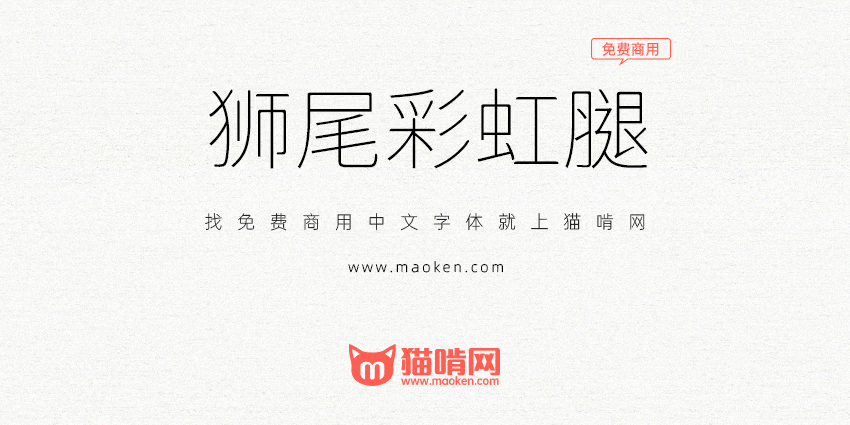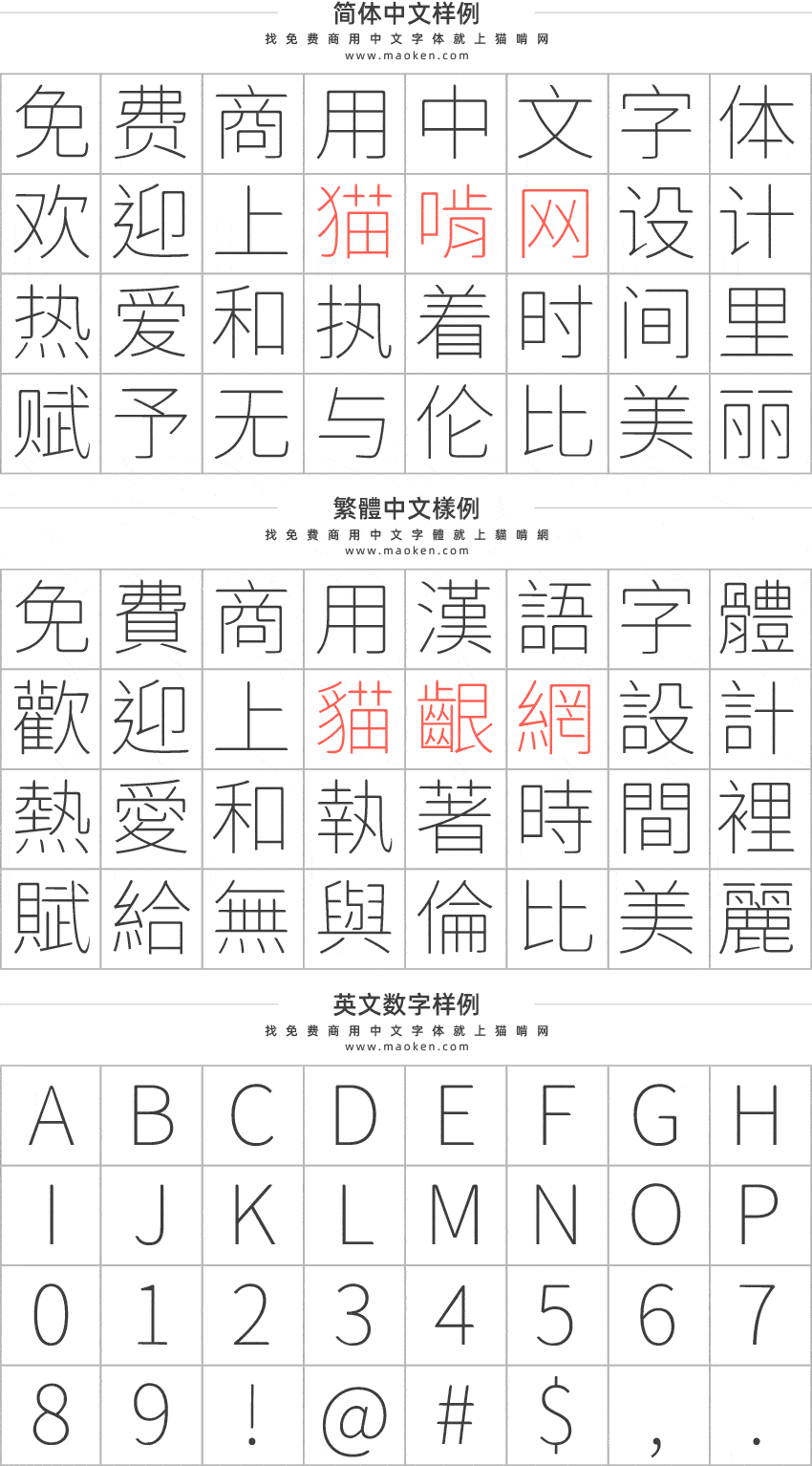
狮尾彩虹腿是一款基于思源黑体的上半边进行变圆改造,更加简明现代化的字体。支持简体中文、繁体中文、韩文与日文;欢迎大家自由应用、自由优化、自由改作!
狮尾彩虹腿的特色是,上半边圆体+下半边黑体,一个综合的字体,“口”字的上沿有一点点像彩虹形状,所以Max把这款字体命名为狮尾彩虹腿。由于这款字体是通过程序自动生成,所以有些字可能会出现问题。相较于原版的思源黑体,可能有误删一些符号或不常用的字。
狮尾彩虹腿是基于思源黑体改造而成,所以无论是简体还是繁体基本上都不缺字,并且拥有7个字重。